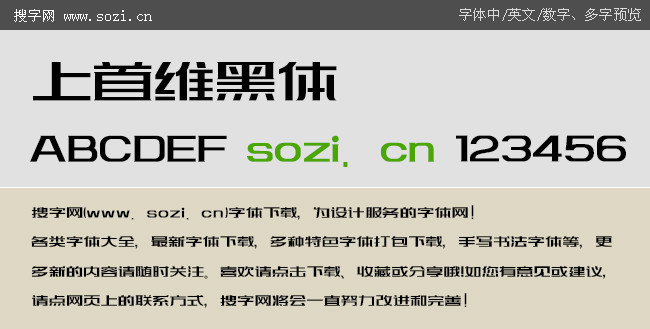
上首維黑體
搜字網(wǎng)給大家提供一款上首維黑體中文字體下載,上首維黑體,字體風(fēng)格穩(wěn)重呈方塊形,字體筆畫豎折處細(xì)節(jié)處理,是此套字庫的亮點(diǎn)。字庫整體特征堅(jiān)硬、有力,具有現(xiàn)代、國際化的指向性,適用于搭配標(biāo)志、廣告標(biāo)語、商業(yè)廣告等高端屬性。